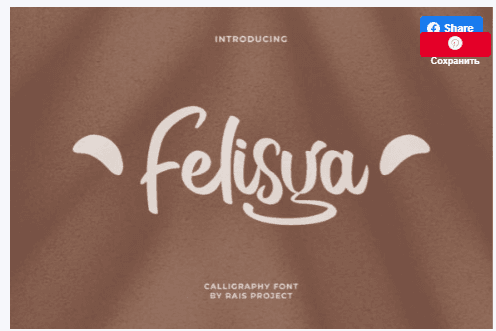
Felisya Script Font
Felisya Script - прекрасный, нежный и милый рукописный шрифт. Этот шрифт закодирован в кодировке PUA, что означает, что вы можете легко получить доступ ко всем глифам и штрихам! Влюбитесь в его невероятно универсальный стиль и используйте его для создания впечатляющих дизайнов!